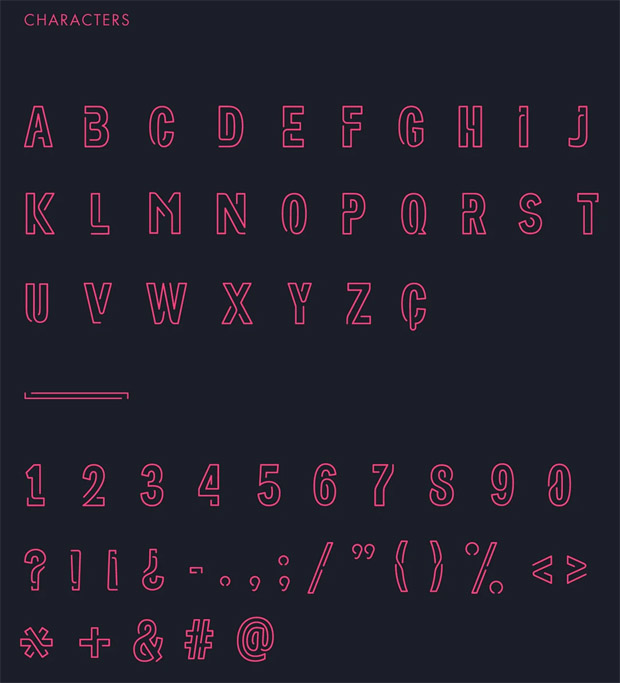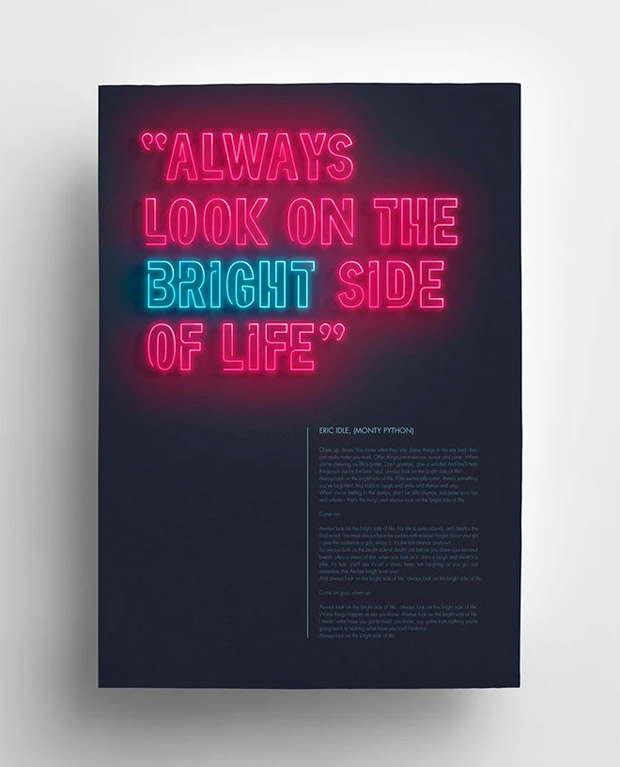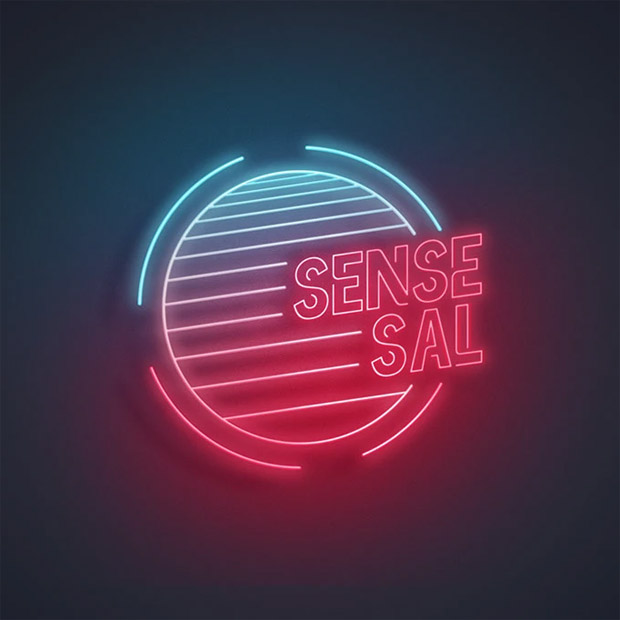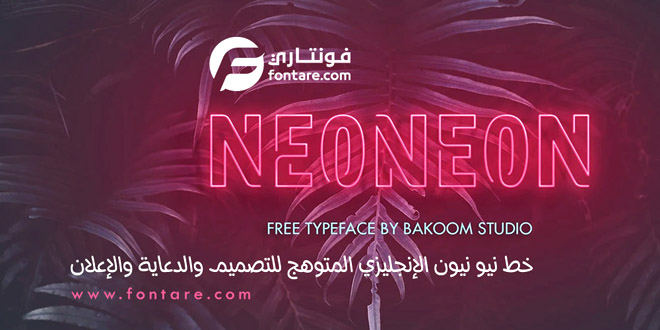
خط نيو نيون الإنجليزي المتوهج للتصميم والدعاية والإعلان .. هو ببساطة خط ذو طابع نيون، يظهر بأفضل صورة عند إضفاء تأثير التوهج عليه، خاصة في برنامج الفوتوشوب، وهو خط متعدد الاستخدامات يُحاكي أسلوب اللافتات في ثمانينيات القرن الماضي. يُمكن استخدامه في الإعلانات، والتغليف، وتصميم الملصقات، وغيرها.